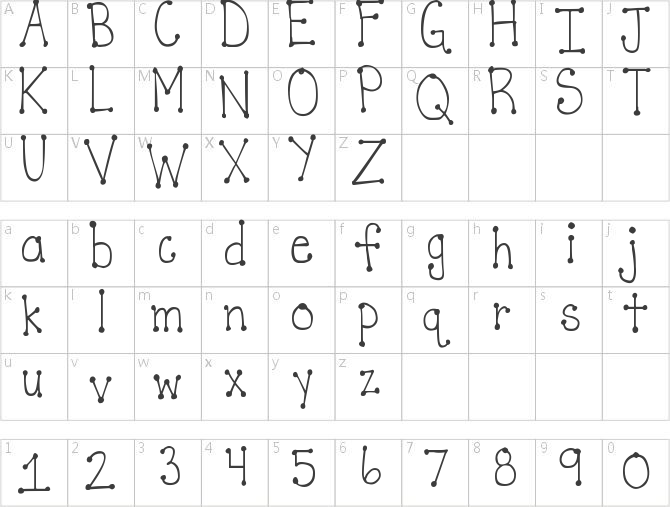
DJB It's Full of Dots Straight 詳情頁
DJB It's Full of Dots Straight
DJB It's Full of Dots Straight介紹
DJB It's Full of Dots Straight字體字庫是一款讓人賞心悅目、百看不厭的英文字體,適合各類廣告和產品包裝設計應用,字體大小0.02MB,格式為ttf字體,上傳用戶是ㄚòひ慬偶鰢,作者/版權方為未知